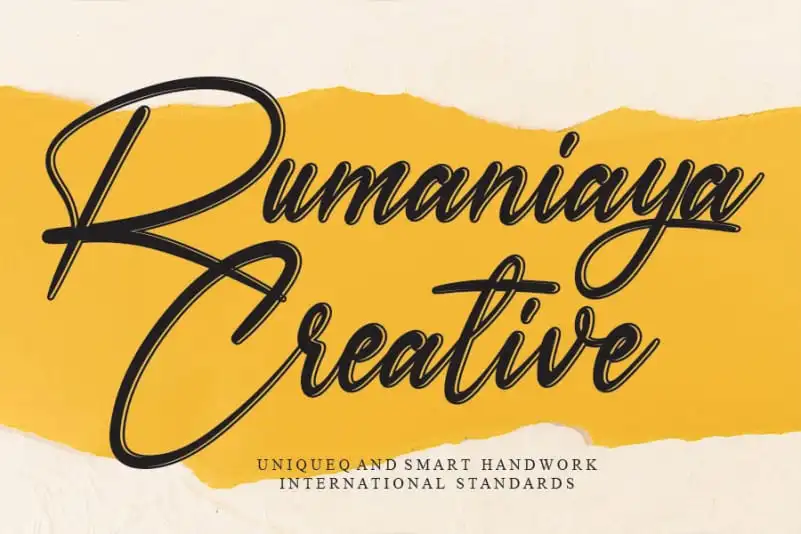
A Rumaniaya Handwritten Font é uma opção perfeita para qualquer designer que busca estilo elegante e autêntico nas criações digitais. Desenvolvida pelo artesão do design andikastudio, ela oferece um toque de sofisticação ideal para diversos projetos criativos. Esta fonte escrita à mão é uma homenagem ao belíssimo e antigo estilo da calligrafia tradicional. Perfeito para designers que desejam dar um toque único e romântico a seus trabalhos, Rumaniaya captura o coração das pessoas com seu charme autêntico. Ideal para criar convites de casamento incrivelmente belos, arte de cartões únicos e sentimentais, postagens chamativas nas redes sociais e cartas de cumprimento adoravelmente fofas. A Rumaniaya Handwritten Font é uma escolha ideal para qualquer designer que busca um toque especial em seus projetos. Seja para eventos importantes ou simples cartas de agradecimentos, esta fonte escrita à mão oferece uma variedade de possibilidades criativas e encantadoras.